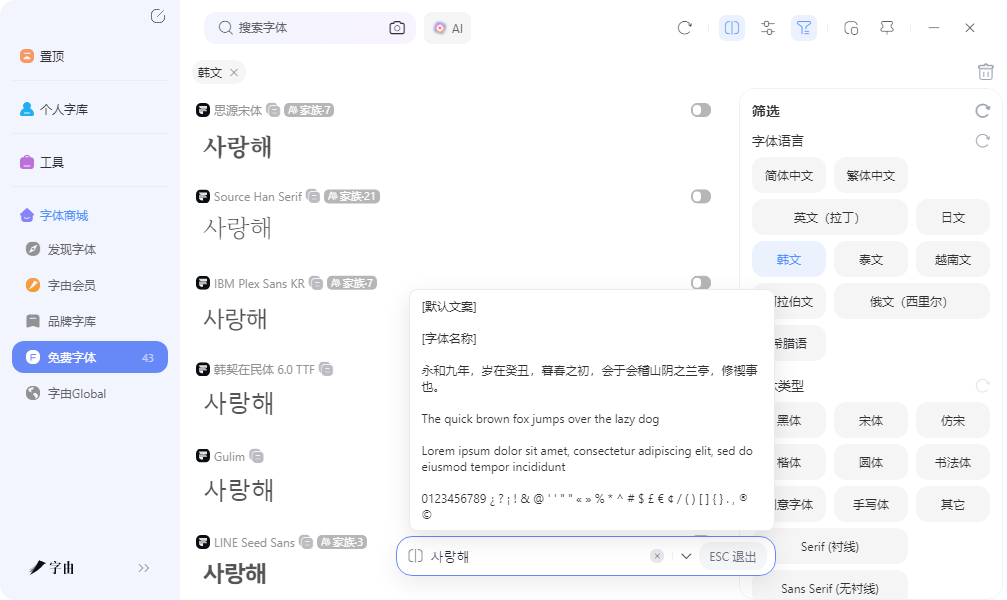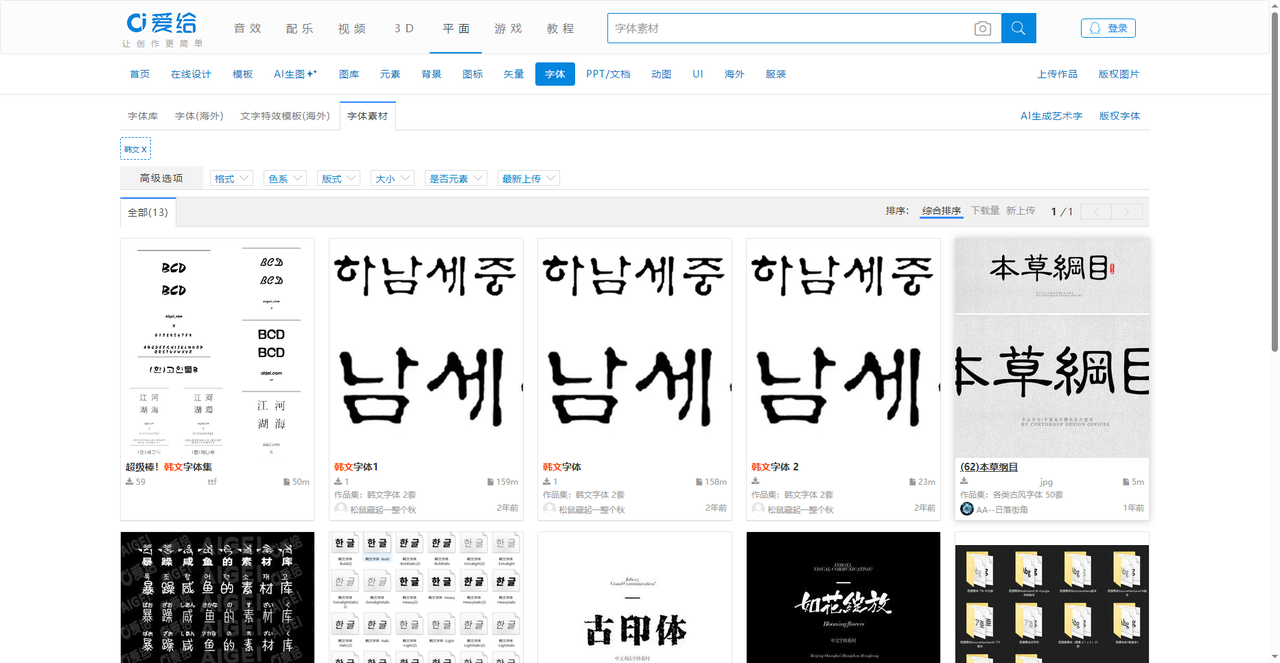
做设计需要韩文字体却不知道去哪里找?这一篇给你答案
韩流文化席卷全球,韩妆、韩剧、韩式餐饮、K-pop周边设计需求越来越大。做一张韩系风格的海报,或者给客户设计一款韩妆品牌的包装,如果没有合适的韩文字体,整个调性就差了。网上搜“韩文字体”,出来的结果要么是乱码,要么是收费的商用字体,要么根本找不到下载入口。其实,有几个地方藏着不错的韩文字体资源,有免费的、有商用的、有可以直接激活使用的。这篇文章整理了6个渠道,从字由到韩文垂直资源站,按需选用。
字由作为综合性字体管理平台,对韩文字体的支持做得比较到位。在字由客户端或网页版的筛选功能里,你可以很容易地找到韩文字体。打开字由客户端,在左侧筛选栏中找到“字体语言”,勾选“韩文”。系统会自动列出字由收录的71款韩文字体(截图显示71款字体等待你发现)。这些字体涵盖了黑体、宋体、圆体、手写体、创意体等多种风格,可以满足从正文排版到标题设计的不同需求。
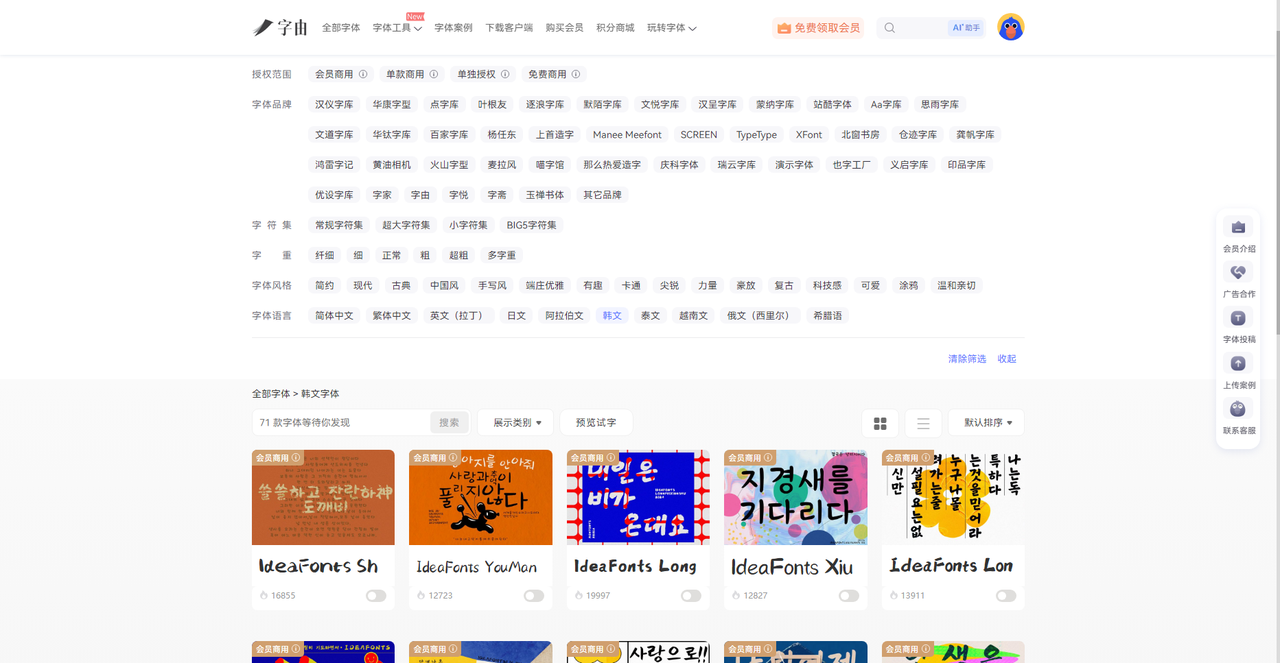
每款字体都标注了授权类型:会员商用、单款商用、单独授权、免费商用等。例如截图中的“IdeaFontsSh”“IdeaFontsYouMan”“IdeaFontsLong”“IdeaFontsXiu”“IdeaFontsLon”等,每款都标注了“会员商用”,并且有使用热度数据。
字由还提供了字体预览功能:输入你自己的韩文文案(比如品牌名“사랑해”或一句标语),可以实时看到字体的实际效果,不用激活就能判断合不合适。如果你需要一款免费的商用韩文字体,可以在筛选栏里再勾选“免费商用”,看看有没有符合的选项。目前字由的免费商用字体库中已经收录了一些开源韩文字体,如Noto Sans KR等。
2、爱给
3、下载字体网
第三个网站是下载字体网。它是一个专门收集“免费商用字体”的网站,首页有明确的分类导航:简体、繁体、英文、日文、韩文。点击“韩文”,就能看到所有免费商用的韩文字体列表。页面展示了“LINE Seed Sans KR Bold”“LINE Seed Sans KR”“HCRDotumLVT-韩文”“首尔汉江体-韩文”“首尔南山体”“思源黑体-韩文版”“思源宋体-韩文版”等多款字体。这些都是知名度较高的免费商用韩文字体。例如LINE Seed Sans KR是LINE品牌推出的免费字体,适合现代感的设计;首尔汉江体和首尔南山体是首尔市政府推出的免费字体,品质高且授权开放;思源黑体和思源宋体的韩文版则是Adobe和Google联合开发的开源字体,可放心商用。每款字体都有预览和下载按钮。点击下载即可获得TTF或OTF文件,安装后使用。这个站的优点是所有字体都明确标注“免费商用”,省去了用户自己确认版权的麻烦。适合做商业项目的设计师。
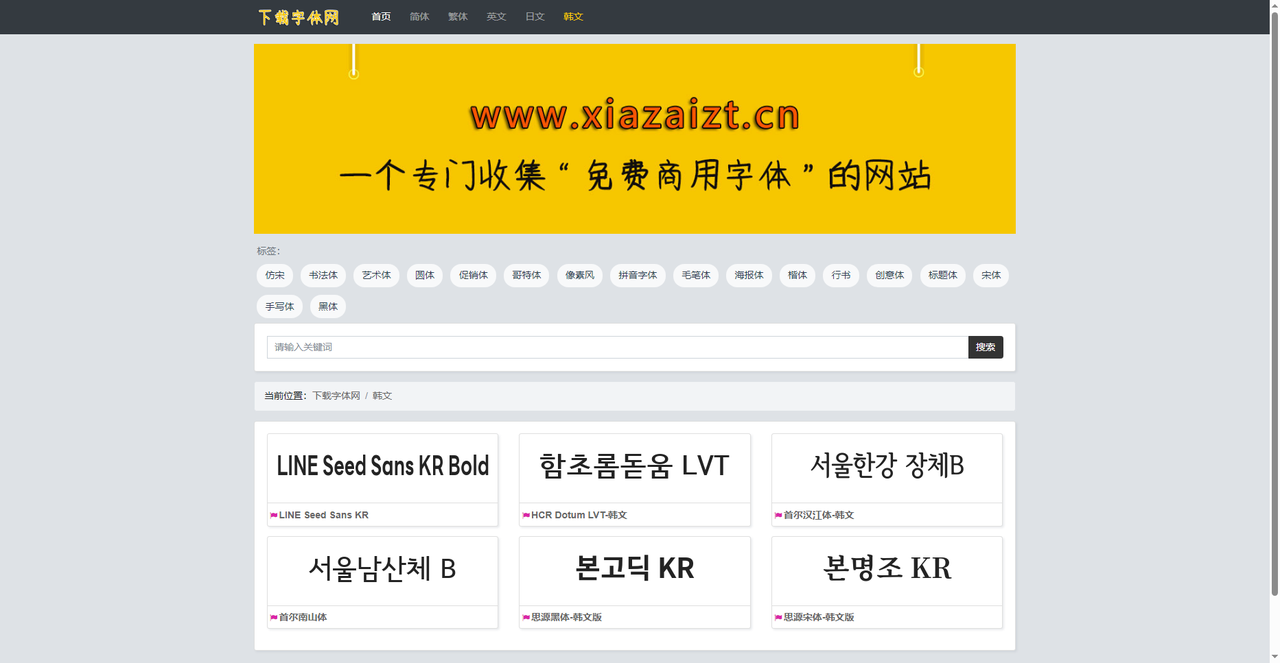
4、自由字体网站
第四个网站是自由字体。它是一个公益性质的字体项目,提供完全免费的字体下载。首页有语言筛选(简体、繁体、英文、日文、韩文)和风格筛选(黑体、仿宋、书法体、手写体、艺术体等)。在韩文字体板块,展示了“LINE Seed Sans KR”“HCR Dotum LVT”“首尔汉江体”“首尔南山体”“思源黑体-韩文版”“思源宋体-韩文版”等。每款字体旁边有“下载”按钮和“韩文”标签。点击下载获取字体文件。这个站的风格简洁,专注于免费字体,没有任何广告干扰。推荐需要高质量免费商用韩文字体的设计师使用。
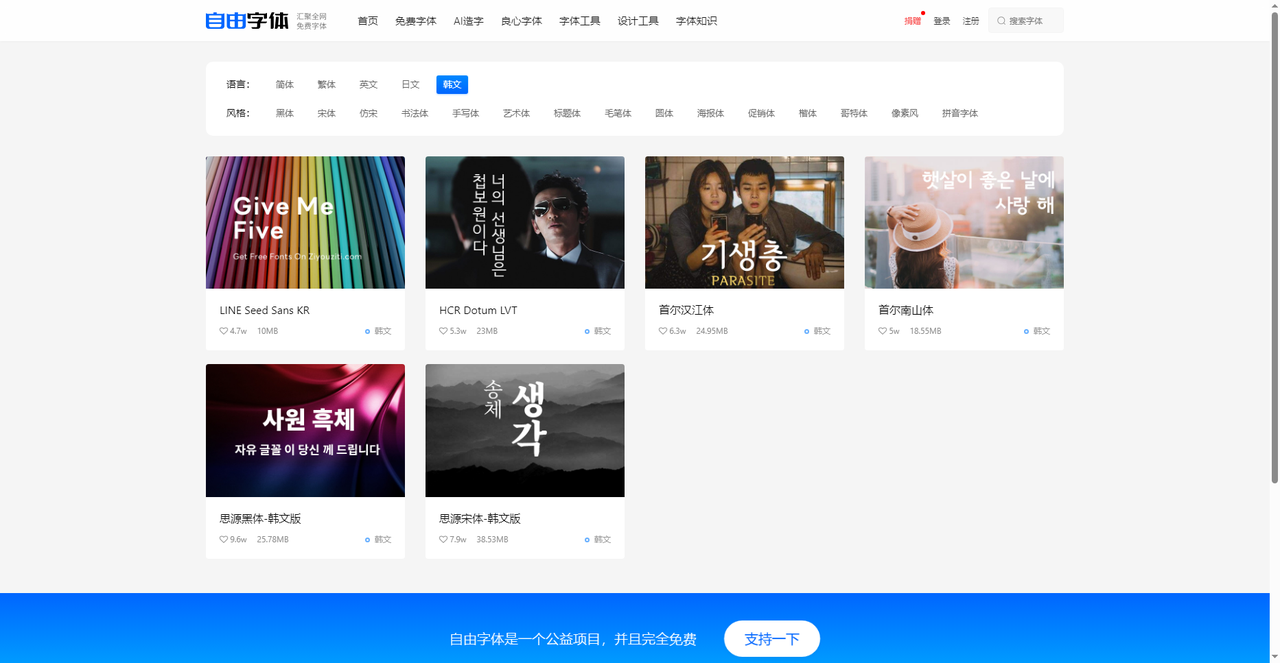
5、Font Meme
第五个网站是Font Meme。这是一个字体识别和资源聚合平台。在它的字体分类中,有“韩文”专项。页面展示了“SFHambakSnowsnowfrost”等字体,并标注了“非拉丁文、中日韩、免费商用、韩文”等标签,明确说明该字体可免费商用。Font Meme的界面比较简洁,点击字体名称可以进入详情页,查看预览和下载链接。这个站的字体数量不算多,但胜在分类清晰、授权标注明确。适合那些想要快速确认字体能否商用、不想花太多时间筛选的用户。
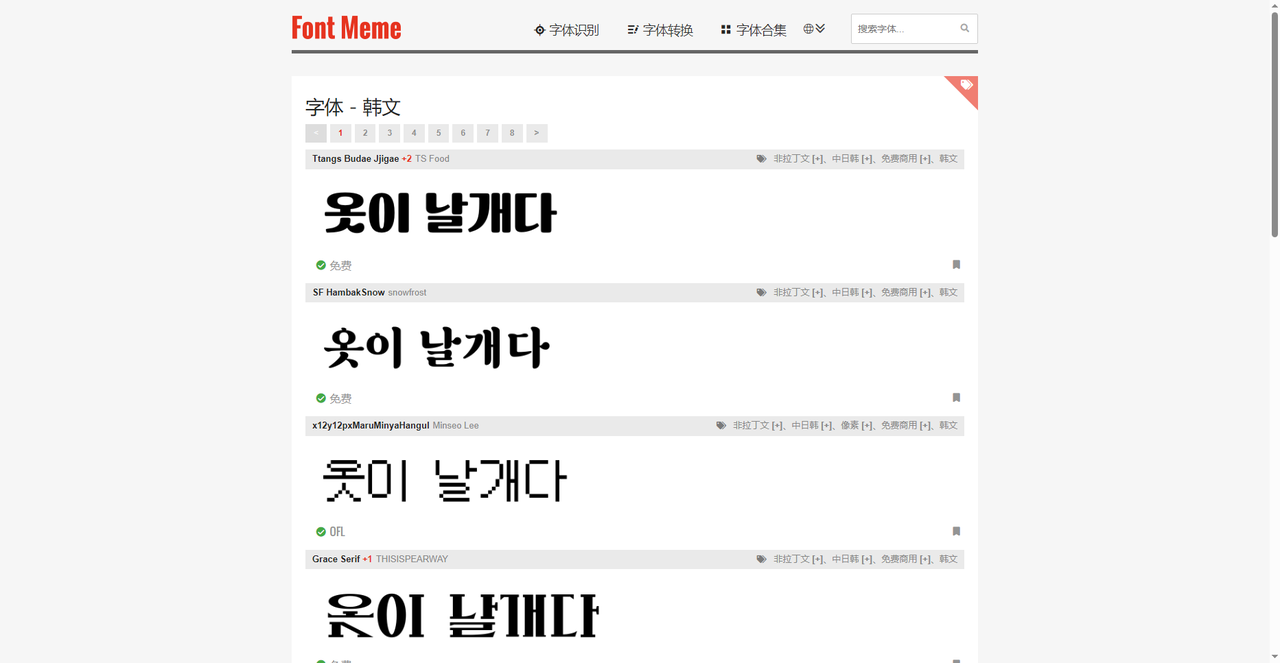
除了以上五个主要渠道,还有一些通用的字体平台也收录了韩文字体。例如Google Fonts中有Noto Sans KR、Nanum Gothic等免费开源韩文字体;Adobe Fonts也有韩文字体可供Creative Cloud用户使用。但是不论如何,字由最适合专业设计师,筛选精准、授权清晰、一键激活使用,无论你是追星做周边,还是正经做品牌设计,总有一个渠道能帮你找到合适的韩文字体。下载前记得确认授权类型,商用项目优先选用免费商用字体。